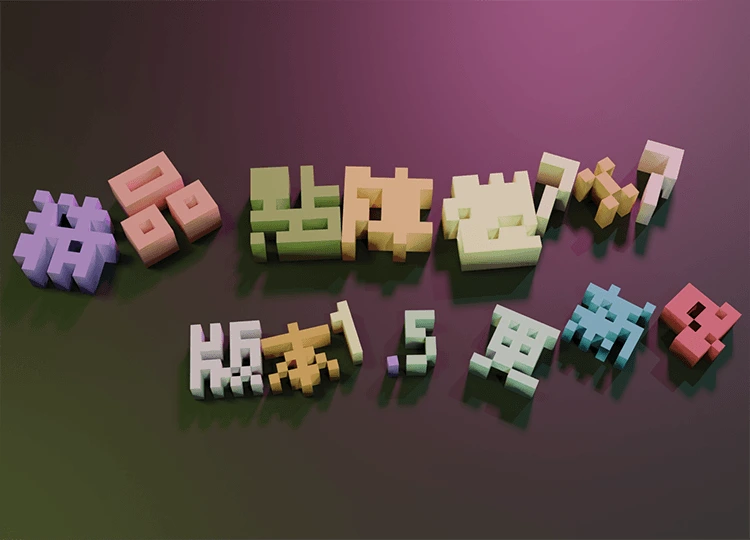
精品点阵体 7x7 Circle Dot
别称:BoutiqueBitmap7x7 Circle Dot / 精品點陣體 7×7 Circle Dot
BoutiqueBitmap7x7/精品點陣體7×7/精品点阵体7×7
《精品點陣體7×7 (BoutiqueBitmap7x7) 》是一款基於美咲フォント改作的字型,目的為適合在繁體中文環境中使用。我們改正了一些標點符號、日本習慣寫法、增加大量字符,使字型使用更方便! 這是一款帶有極強烈的點陣風格的字型,非常適合用在像素畫、遊戲相關主題等等。